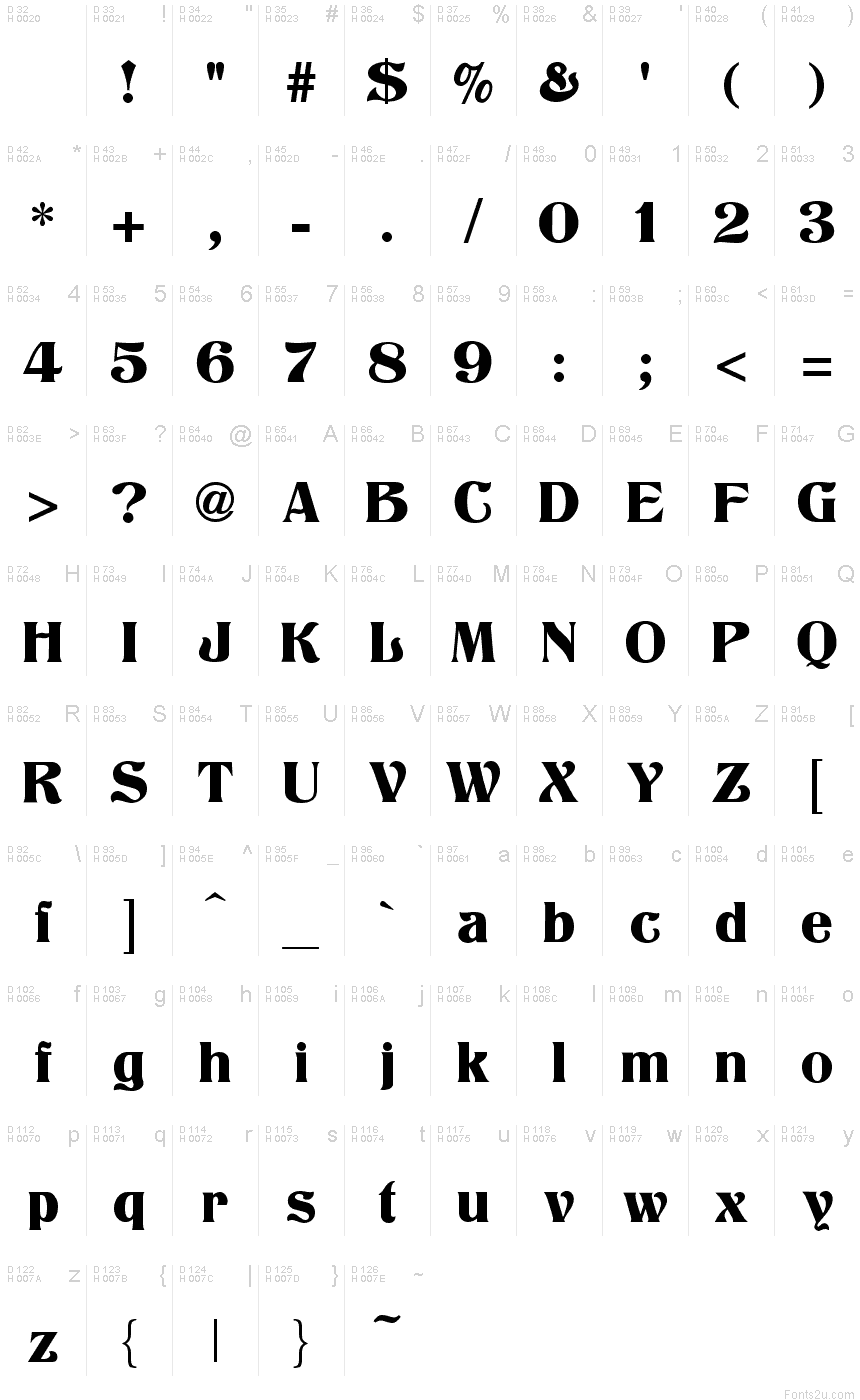
Podgląd czcionki Titania
Titania autorstwa Richarda Williama Muellera to darmowy, kontrastowy krój szeryfowy z 1993 roku o bogatym, nieco baśniowym charakterze. Litery łączą ostre, zamaszyste szeryfy z miękkimi, pełnymi krzywiznami, dzięki czemu krój sprawia wrażenie formalnego, ale nie jest sztywny.
Dzięki temu jest to naturalny wybór na okładki książek, nagłówki w magazynach, plakaty, branding butików oraz karty tytułowe, gdzie przydaje się odrobina teatralnej gracji. Świetnie sprawdza się również w krótkich nagłówkach i inicjałach typu monogram, ponieważ szerokie łuki i zwężane połączenia nadają nawet kilku literom wyrazistą, dekoracyjną formę.